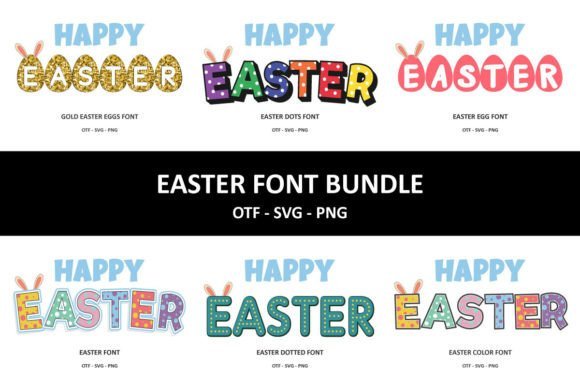
Easter Bundle Font
Easter Bundle Font – حزمة الخطوط الاحترافية لعيد الفصح
أضف لمسة إبداعية ساحرة إلى تصاميمك الاحتفالية مع Easter Bundle Font، حزمة خطوط مميزة مستوحاة من أجواء عيد الفصح المبهجة. تتميز هذه الحزمة بتصاميم أنيقة ومرحة تناسب مختلف الاستخدامات، مثل:
تم تصميم Easter Bundle Font بجودة عالية لتضمن لك تجربة استخدام سلسة على مختلف البرامج والتطبيقات. اجعل تصاميمك تنبض بالحياة مع هذه المجموعة الفريدة! ????????